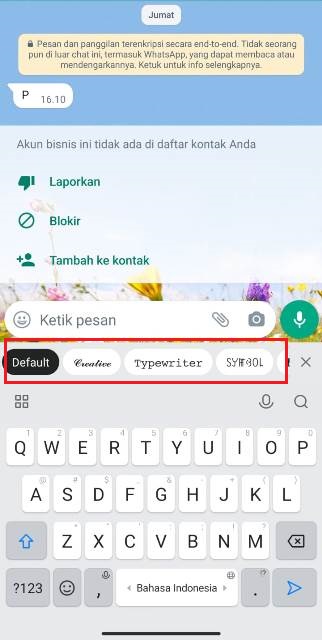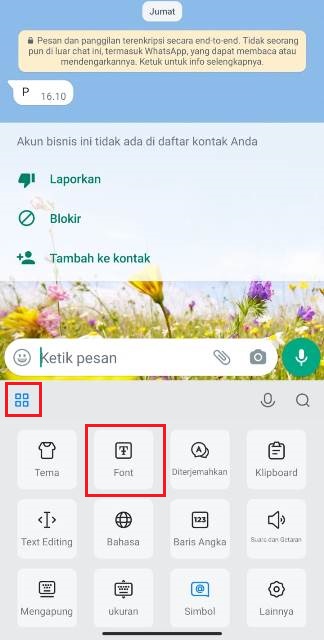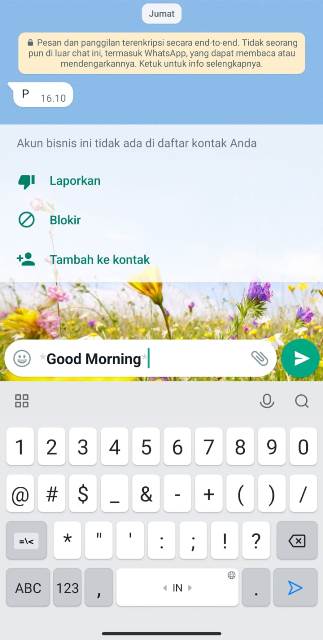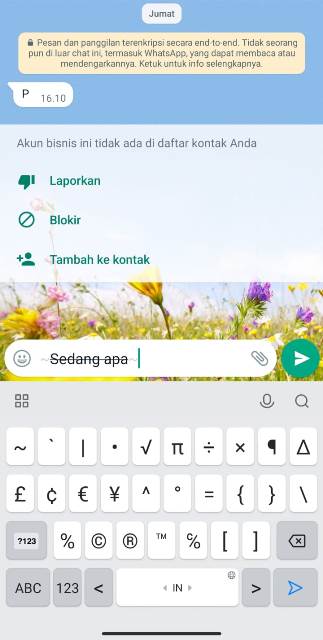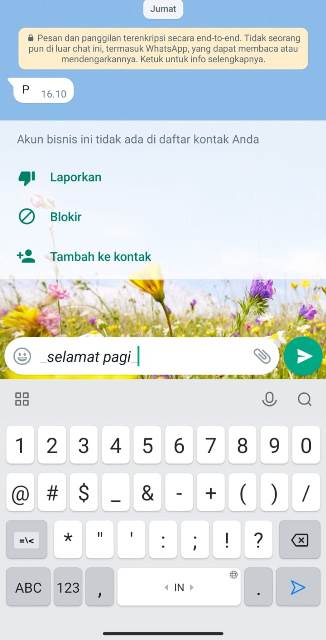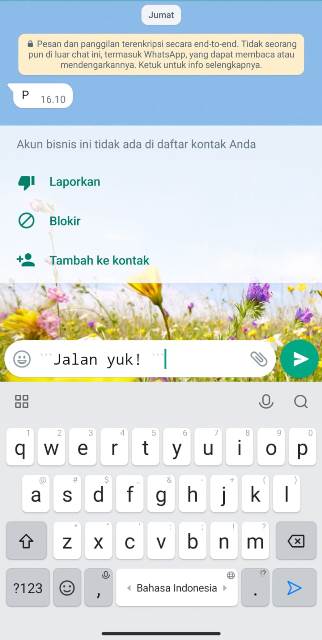
Cara Mengganti Font WhatsApp Tanpa Aplikasi, Dijamin Keren!
Cara Mengganti Font WhatsApp
Cara mengganti font WhatsApp (WA) bisakah tanpa perlu menginstall aplikasi tambahan? Pastinya kamu penasaran dengan jawab dari pertanyaan tersebut.
Jawabanya tentu bisa, guys. Bahkan ada sejumlah metode yang bisa kamu praktikkan untuk membuat font WhatsApp beda dari biasanya.
Dengan font yang lebih keren, pastinya chatting juga akan lebih seru.
Sebagai informasi, aplikasi WhatsApp memang menawarkan sejumlah format font yang dapat kalian gunakan. Di antaranya adalah Bold, Italic, Coret, dan Monoscape.
Untuk menggunakan beberapa font tersebut, tentu ada kode tertentu yang harus kamu ketahui. Kami pun bakal membahasnya pada artikel ini.
Selain itu, ada juga cara lain untuk mengubah font di WhatsApp tanpa aplikasi. Dan tutorialnya akan sekalian kami bahas, jadi akan banyak informasi yang kamu dapatkan jika membaca artikel ini sampai selesai.
Terkadang beberapa pengguna WhatsApp merasa bosan dengan model font yang itu-itu saja. Mereka pun menginginkan sesuatu yang baru agar chat semakin seru dan tidak monoton.
Nah, kamu bisa memilih salah satu atau bahkan mempraktikkan semua cara ganti font di WhatsApp berikut ini yang bisa dilakukan tanpa perlu aplikasi.
Cara Mengganti Font WhatsApp Tanpa Aplikasi
Langsung saja, berikut ini tata cara ubah font WhatsApp yang mudah untuk dipraktikkan!
Ubah font dengan menambahkan karakter tertentu
Metode pertama untuk mengubah font di WA adalah dengan menambahkan karakter tertentu. Kami pun sudah membahas di awal tadi, yakni font tebal, miring, coret dan karakter blok atau monoscape.
Untuk bisa mengubah font menjadi keempat jenis font tersebut, kalian harus menambahkan tanda tertentu. Dan setiap font pun berbeda tanda yang harus ditambahkannya, guys.
Pertama, mengubah font jadi bold atau tebal layaknya di MS Word. Kamu bisa menggunakan font ini untuk menekankan kata atau kalimat penting ketika mengirim pesan.
Untuk membuat teks teal, kamu hanya harus menambahkan tanda asterik (*) di awal dan akhir pesan. Misalnya, *Good Morning*. Secara otomatis font pun akan berubah jadi tebal.
Font Bold
Kedua, memiringkan huruf atau italic yang biasa digunakan untuk menandai kata asing. Kali ini gunakan garis bawah atau underscore (_) di awal dan akhir teks. Contohnya, _Selamat Pagi_
Font Italic
Ketiga, mencoret atau strikethrough. Kamu bisa menggunakannya untuk mengoreksi kesalahan pada pesan. Cara membuatnya, tambahkan tanda tilde (~) di awal dan akhir kalimat. Contohnya, ~Sedang apa?~
Font Coret
Keempat sekaligus juga yang terakhir adalah karakter blok. Tambahkan tanda backtick (`) sebanyak tiga kali di awal dan akhir teks. Contohnya, “`Jalan yuk!“`
Font Monoscape
Lewat situs
Jika kamu ingin mengubah teks menjadi lebih beragam dari keempat model font di atas, bisa juga memanfaatkan situs font generator.
Cara penggunaannya sangat mudah, kamu hanya perlu mengunjungi situsnya, misalnya Cool Symbol lalu ketik kata atau kalimat sesuai keinginan.
Font Generator
Salin teks pada font yang kamu pilih. Setelahnya, paste teks tersebut di obrolan WhatsApp untuk kemudian dikirimkan.
Mengganti font WhatsApp pakai keyboard
Selain dengan beberapa metode di atas, cara mengganti font di WhatsApp berikutnya adalah menggunakan font yang ada di keyboard.
Pada sejumlah keyboard terdapat fitur font, sehingga pengguna bisa memanfaatkannya saat chatting agar lebih menarik.
Tak melulu harus menginstall keyboard di Play Store, kita bisa meggunakan keyboard yang sudah tersedia secara default di HP.
Contohnya di sini kami menggunakan keyboard yang sudah tersedia di HP Xiaomi. Silakan klik icon di pojok kiri atas keyboard, lalu klik Font untuk mengaktifkan fitur font.
Cara Mengganti Font di WhatsApp
Selanjutnya pilih dan klik jenis font yang diinginkan. Setelahnya kamu pun bisa langsung menggunakannya untuk chatting.